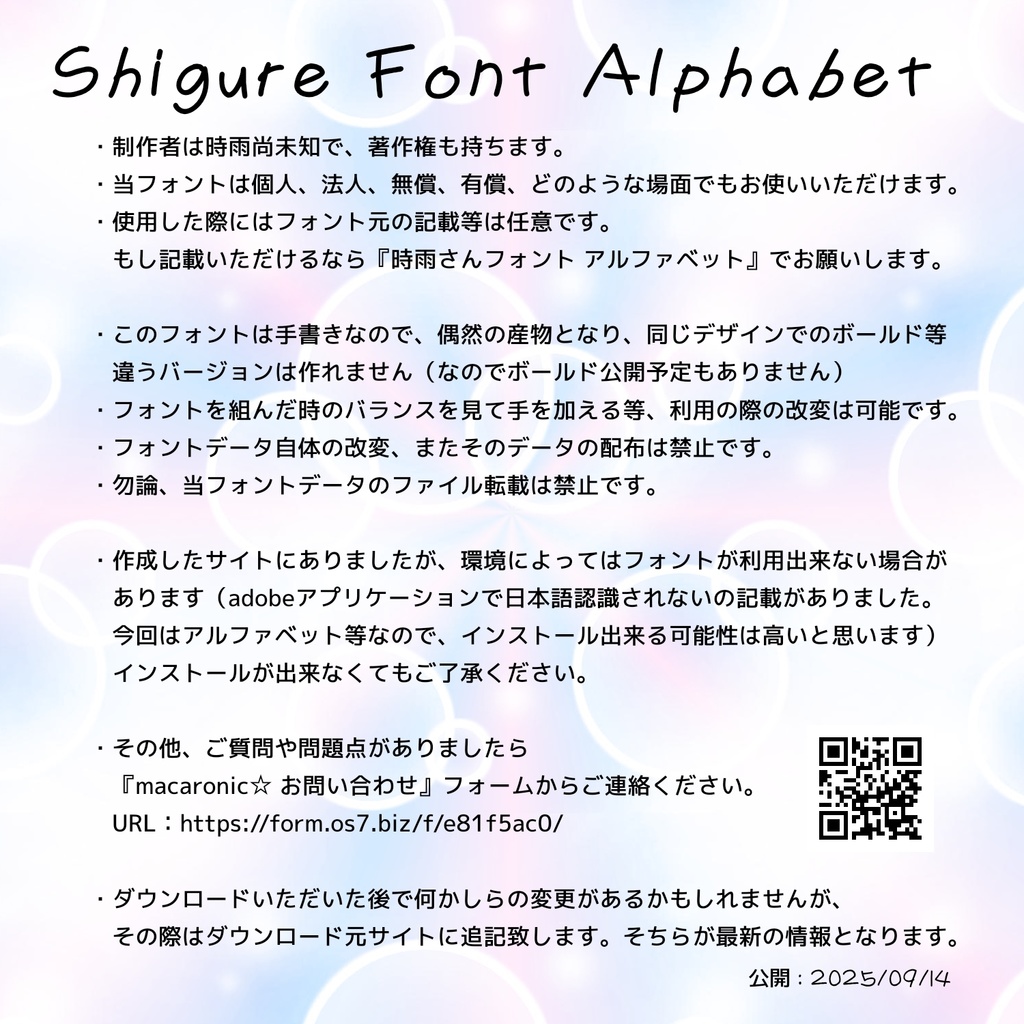
時雨さんフォント アルファベット
時雨尚未知が手書きして作成したフォントです。 「フォントを書こう! by 字嗨( https://buttaiwan.github.io/writemyfont/ja.html )」を利用して作成しました。 フォント内容:アルファベット(大文字/小文字)他記号 ※詳しくは画像を参照ください 《 注意事項 》 ・時雨尚未知が著作権を持ちます(問題があったら、まず連絡は私にください) ・フォントは凄く細いです。でもボールド(太い)等の同じデザインの差分フォントを出す予定はありません ・個人、法人、無償、有償、どのような場面でもお使いいただけます ・半角でも全角でも同じデザインのアルファベット等が出ます(半角「A」全角「A」のように細長い/大きいはない)その代わり、全角では縦書きにも対応しています(いました) ・フォントデータの無断配布や改変(またその改変データの配布)は禁止です ・フォントデータを使用してのレイアウト上の修正や改変等は問題ありません